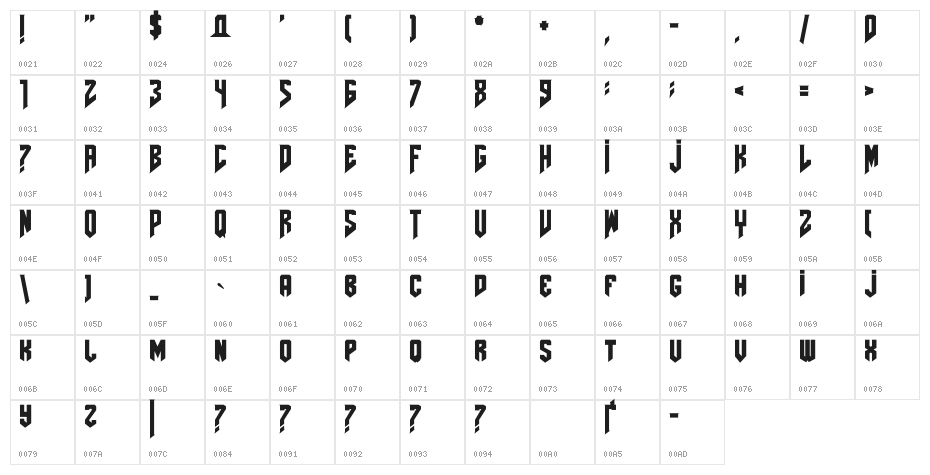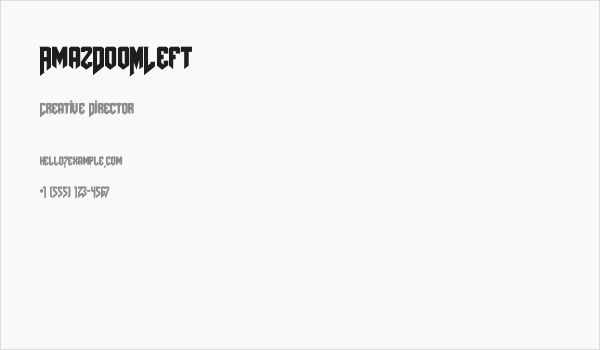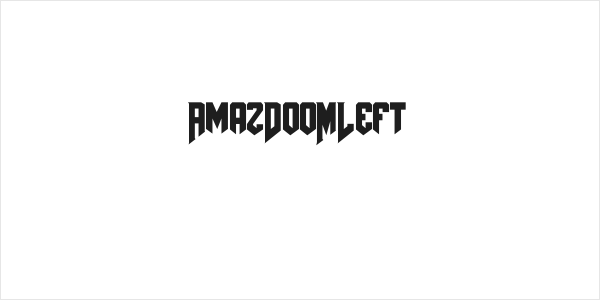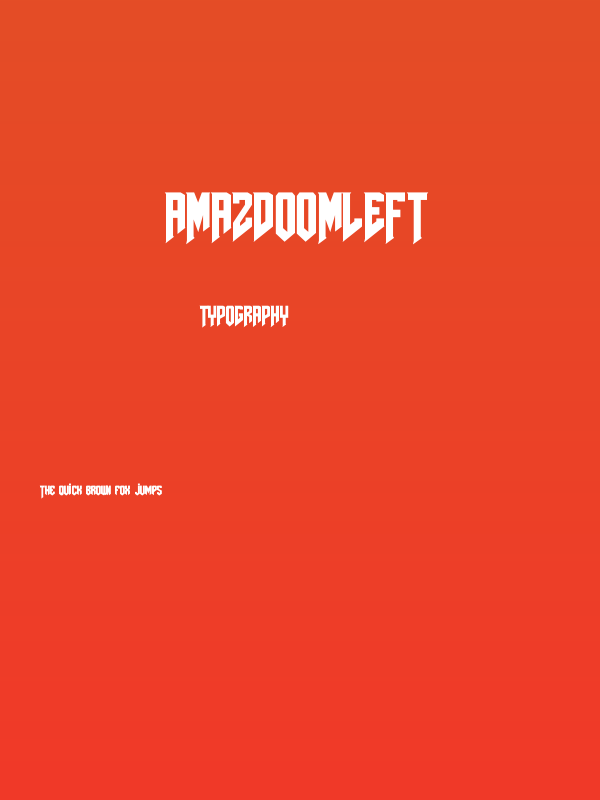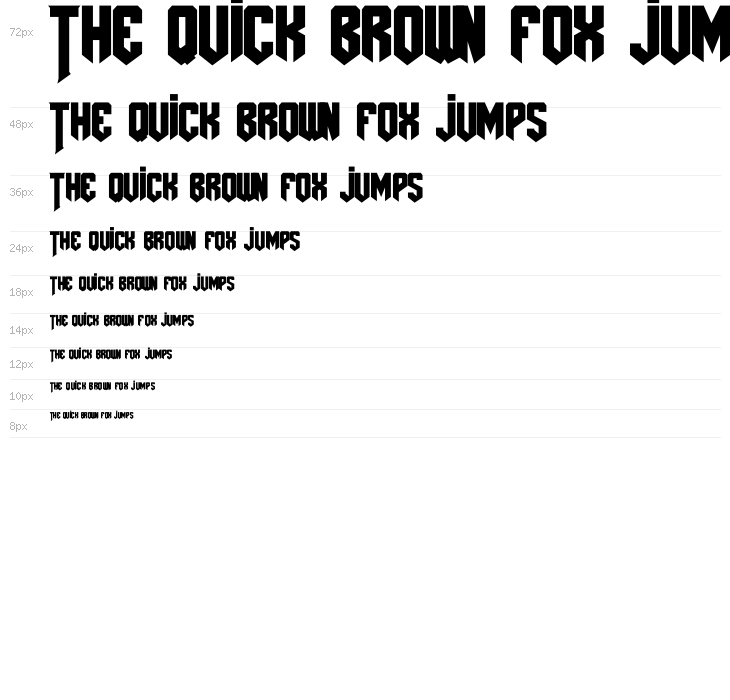
AmazDooMLeft Font
| 全体的なスタイル | Futuristic |
| おすすめプロジェクト | Ideal for video game titles, movie posters, or any project requiring a strong, impactful visual presence. |